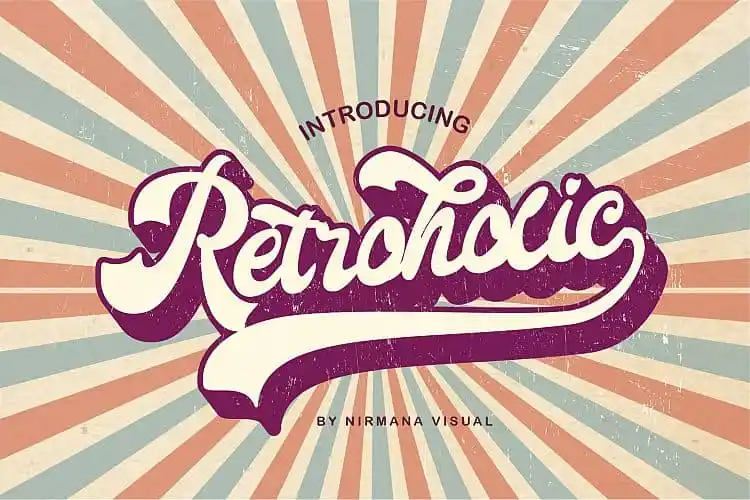
Na categoria de script fonts, a retroholic Retro Font apresenta uma experiência visual encantadora inspirada nos anos 70 e 80. Criada para designers apaixonados por estilo retrô combinado com a delicadeza do lettering manual, esta fonte oferece uma harmonia tipográfica única que se adapta perfeitamente a um vasto leque de projetos gráficos. Perfeita tanto para criar logomarcas e estilos de marca, como posts nas mídias sociais, anúncios ou design de produtos, retroholic Retro Font é uma escolha ideal para aqueles que valorizam o charme nostálgico dos anos 70 e 80 em suas criações. Através do seu estilo retrô renovado, a fonte convida os designers a experimentar um novo olhar sobre as letras que transforma simples textos em obras de arte encantadoras.